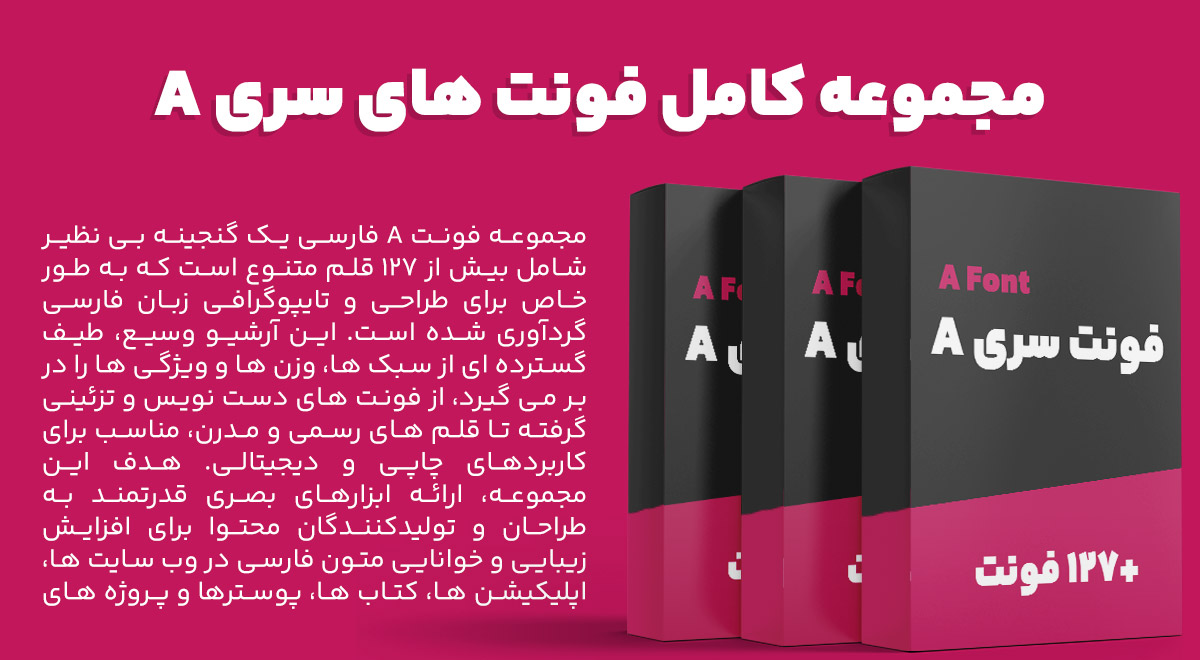
مجموعه فونت A فارسی (+127 فونت)
مجموعه فونت A فارسی یک گنجینه بی نظیر شامل بیش از ۱۲۷ قلم متنوع است که به طور خاص برای طراحی و تایپوگرافی زبان فارسی گردآوری شده است. این آرشیو وسیع، طیف گسترده ای از سبک ها، وزن ها و ویژگی ها را در بر می گیرد، از فونت های دست نویس و تزئینی گرفته تا قلم های رسمی و مدرن، مناسب برای کاربردهای چاپی و دیجیتالی. هدف این مجموعه، ارائه ابزارهای بصری قدرتمند به طراحان و تولیدکنندگان محتوا برای افزایش زیبایی و خوانایی متون فارسی در وب سایت ها، اپلیکیشن ها، کتاب ها، پوسترها و پروژه های برندینگ است. با این فونت ها، می توانید به هر طرحی جلوه ای منحصر به فرد و حرفه ای ببخشید.
مجموعه فونت A فارسی: گنجینه ای از ۱۲۷+ قلم برای طراحی فارسی
مجموعه فونت های سری A فارسی، یکی از جامع ترین و کاربردی ترین آرشیوهای قلم فارسی است که بیش از ۱۲۷ فونت مختلف را در خود جای داده است. این مجموعه با تنوع بی نظیر خود، پاسخگوی نیازهای گوناگون طراحان گرافیک، ناشران، توسعه دهندگان وب و تولیدکنندگان محتواست. فونت های موجود در این سری، شامل طیف وسیعی از سبک ها هستند که هر یک ویژگی های بصری خاصی را به متن شما می بخشند.
در این مجموعه، شما می توانید فونت هایی با سبک های رسمی و کلاسیک مانند “فونت A افسانه”، “فونت A جنت ال تی” یا “فونت A کتاب” را بیابید که برای متون طولانی، مقالات و کتاب ها ایده آل هستند. در کنار آن ها، فونت های مدرن و شیک مانند “فونت A ایران سنس” (با نسخه های رگولار، بولد و ایتالیک) یا “فونت A ناهار” (با وزن های مدیوم، بلک و بولد) نیز حضور دارند که برای طراحی های معاصر، وب سایت ها و اپلیکیشن ها بسیار مناسب اند.
تنوع در این مجموعه تنها به سبک محدود نمی شود، بلکه شامل وزن های مختلف (مانند رگولار، لایت، تین، بولد، بلک و فت) و استایل های متنوع (مانند ایتالیک و نسخه های خاص) نیز می شود. به عنوان مثال، فونت “A دانش” با چهار وزن شامل رگولار، بولد، ایتالیک و بولد ایتالیک، انعطاف پذیری بالایی را در اختیار طراح قرار می دهد.
برای پروژه هایی با جلوه های بصری خاص، فونت های تزئینی و فانتزی مانند “فونت A عارف گرافیتی”، “فونت A خط خطی”، “فونت A سیم خاردار” یا “فونت A پیکسل” (با نسخه های مختلف) در این مجموعه یافت می شوند. همچنین، فونت های دست نویس مانند “فونت A دست نویس” و “فونت A یاسمین” حسی شخصی و هنری به طرح های شما می بخشند.
دانلوداز دیگر فونت های برجسته می توان به سری “A انتظار ظهور” با نسخه های متعدد (از جمله A Entezare Zohoor 1 تا 6 و نسخه های B, C, D با وزن های مختلف) اشاره کرد که پتانسیل های خلاقانه ای را فراهم می آورد. فونت های الهام گرفته از خوشنویسی مانند “فونت A ثلث” و “فونت A نسخ تحریر” نیز برای پروژه هایی با حال و هوای سنتی یا هنری مناسب هستند. حتی فونت های کاربردی مانند “فونت A ماشین تحریر” (با نسخه های قدیمی و بولد) و “فونت A بانک” نیز در این مجموعه موجود هستند که برای پروژه هایی با نیازهای خاص مفید خواهند بود. این مجموعه با فراهم آوردن این گستره وسیع از قلم ها، به طراحان قدرت می دهد تا ایده های خود را به بهترین شکل ممکن به واقعیت تبدیل کنند.
کاربردها: توسعه بصری در پلتفرم های مختلف
مجموعه فونت A فارسی با گستردگی و تنوع خود، ابزاری بی نظیر برای طیف وسیعی از کاربردها در محیط های مختلف دیجیتال و چاپی است.
- طراحی وب و اپلیکیشن: برای وب سایت ها و اپلیکیشن های موبایل، فونت های مدرن و خوانای این مجموعه (نظیر Font A Iranian Sans) به بهبود تجربه کاربری و زیبایی بصری کمک شایانی می کنند.
- نشر و مطبوعات: فونت های رسمی و کلاسیک این مجموعه برای کتاب ها، مجلات، روزنامه ها و گزارش های سالانه، خوانایی و جلوه حرفه ای را تضمین می کنند.